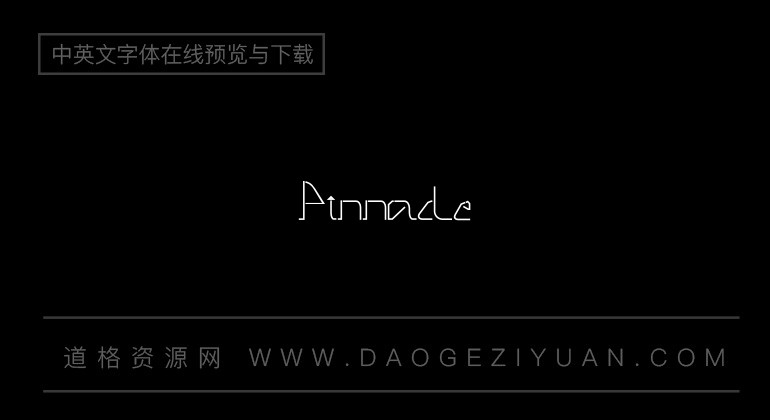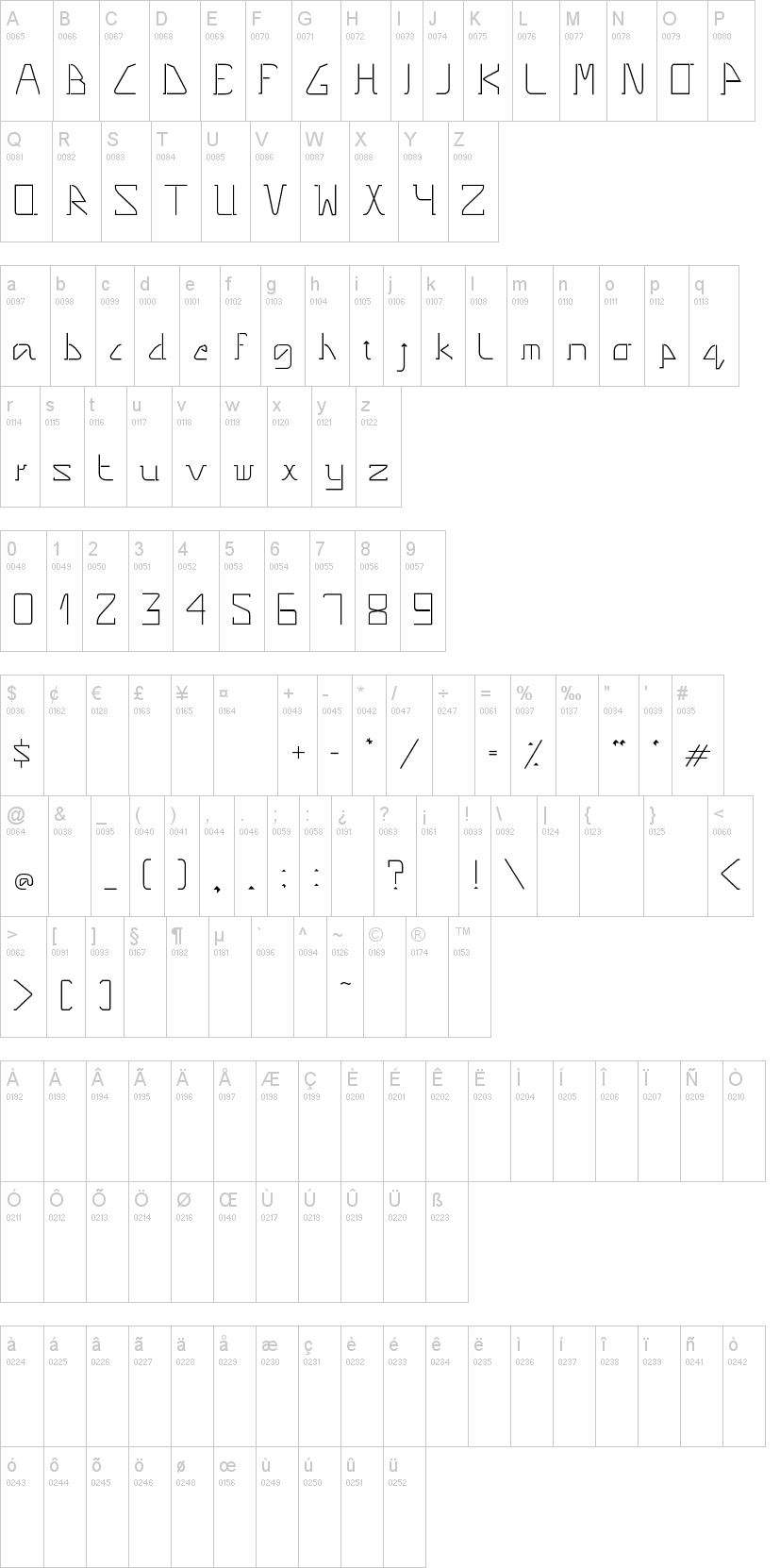
Pinnacle
Pinnacle 字体是一种现代风格的无衬线字体,由设计师 Matthieu Meyer 设计。这种字体具有清晰的线条和简单的结构,使其非常适合用于广告、标志、包装和海报等设计项目中。 Pinnacle 字体的特点包括: 1. 清晰易读:Pinnacle 字体使用简单的线条和形状,使其在各种大小和分辨率下都能保持清晰易读。 2. 现代感:该字体的设计风格非常现代化,使其适用于各种现代化的设计项目。 3. 多种字重:Pinnacle 字体提供多种字重,从普通体到粗体,以适应不同的设计需求。 4. 多语言支持:该字体支持多种语言,包括拉丁字母、西里尔字母和希腊字母等。 总的来说,Pinnacle 字体是一种非常适合于现代设计项目的无衬线字体,其清晰易读的特点和多种字重让它成为了很多设计师的首选。
Pinnacle是一款非常不错的手写艺术字体,具有很好的视觉感,适合于文化类的宣传设计、商业类品牌的广告和产品包装设计以及个性化文字排版等较多场景。